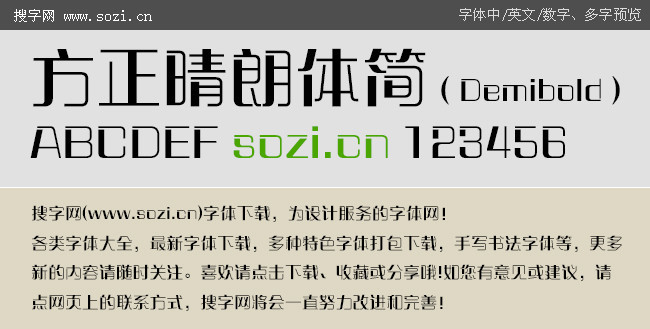
方正晴朗體簡(jiǎn)Demibold
搜字網(wǎng)提供一款方正晴朗體簡(jiǎn)中文字體下載,晴朗體字體爽朗,充滿(mǎn)陽(yáng)光氣息,所以命名為“晴朗體”。 晴朗體普遍每一個(gè)字只有兩直劃是粗的,其余橫直都是細(xì)的,左邊上下直角,右邊上下是圓角,形成一個(gè)強(qiáng)烈對(duì)比,所以粗細(xì)的視覺(jué)很平均,不會(huì)有太重和太輕的感受,排版畫(huà)刊更有舒服感覺(jué),工整中還少許動(dòng)感,美觀齊整,空間分布平均,適合金融、保險(xiǎn)行業(yè),汽車(chē)行業(yè),投資行業(yè),電子產(chǎn)品的商業(yè)宣傳和包裝設(shè)計(jì)!